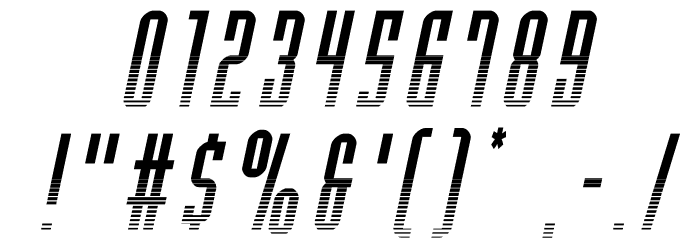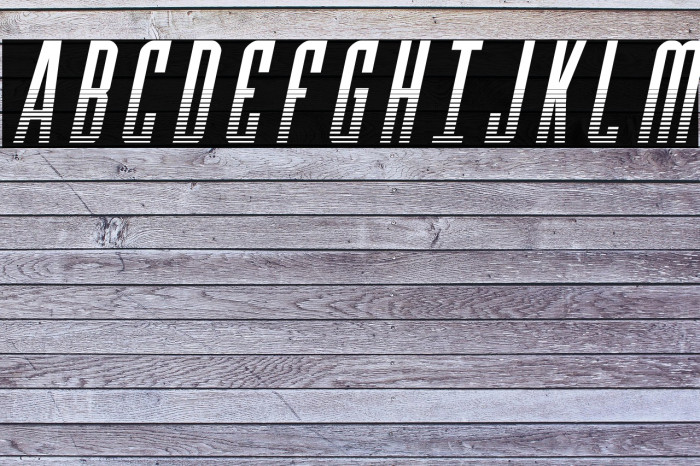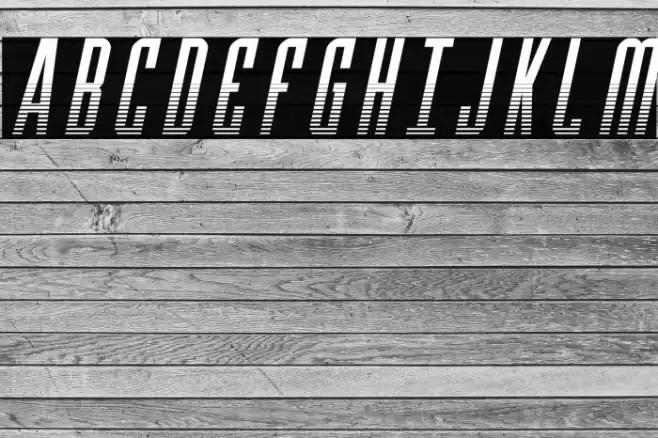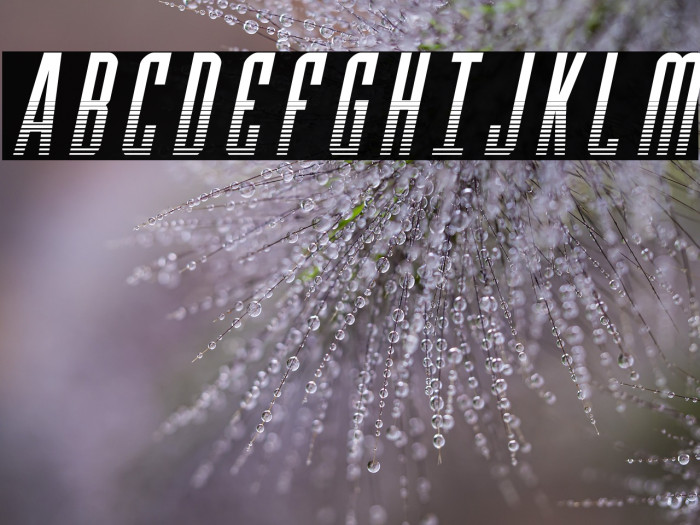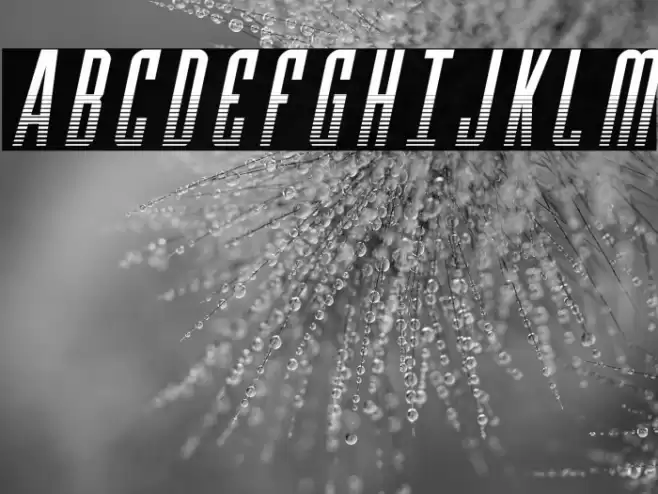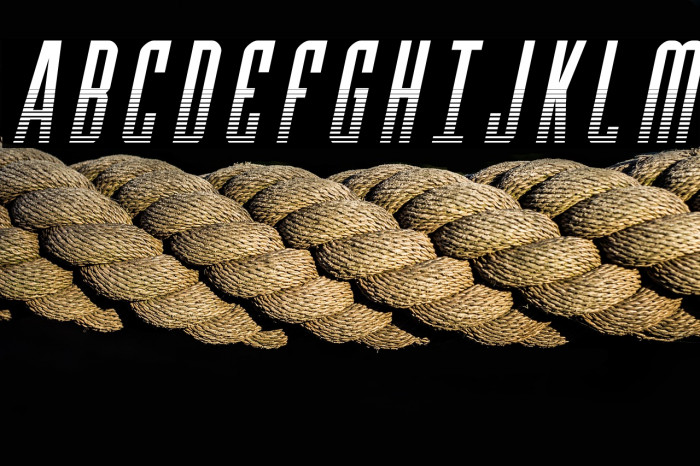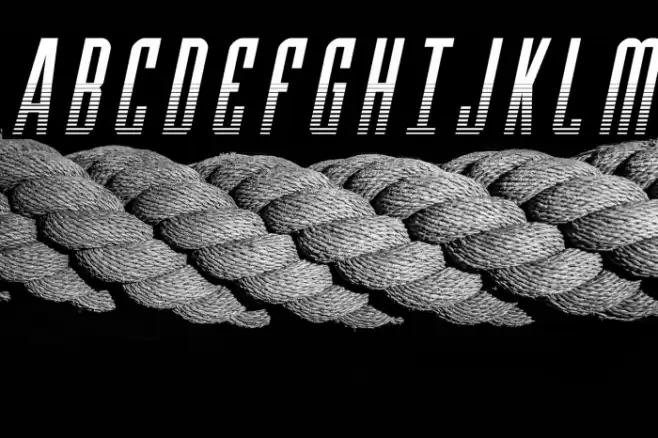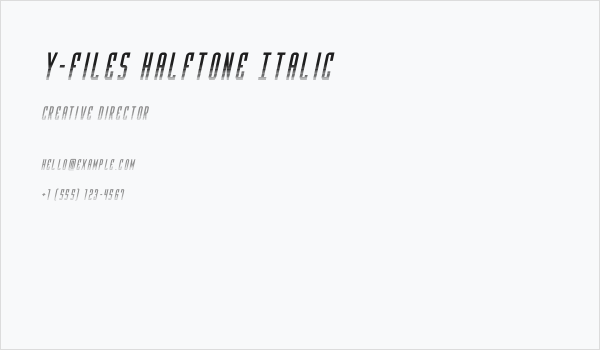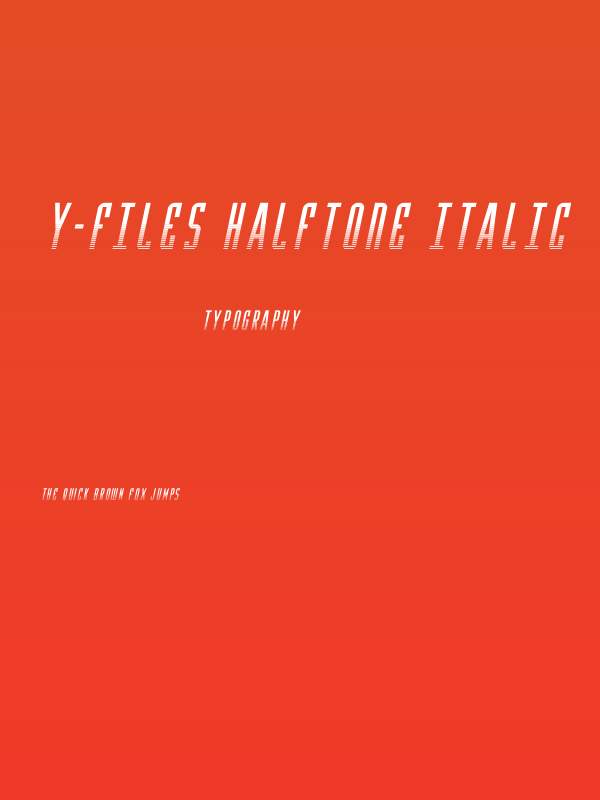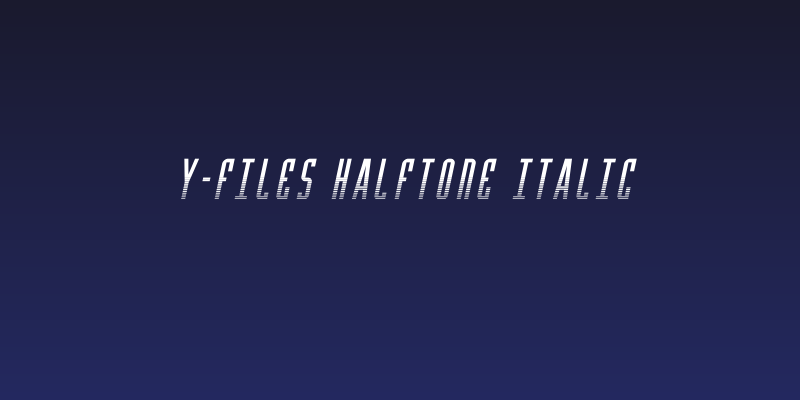
Y-Files Halftone Italic Font
✎ Futuristic
| Рекомендуемые проекты | Ideal for use in technology branding, sports team logos, futuristic posters, and dynamic advertising campaigns. |